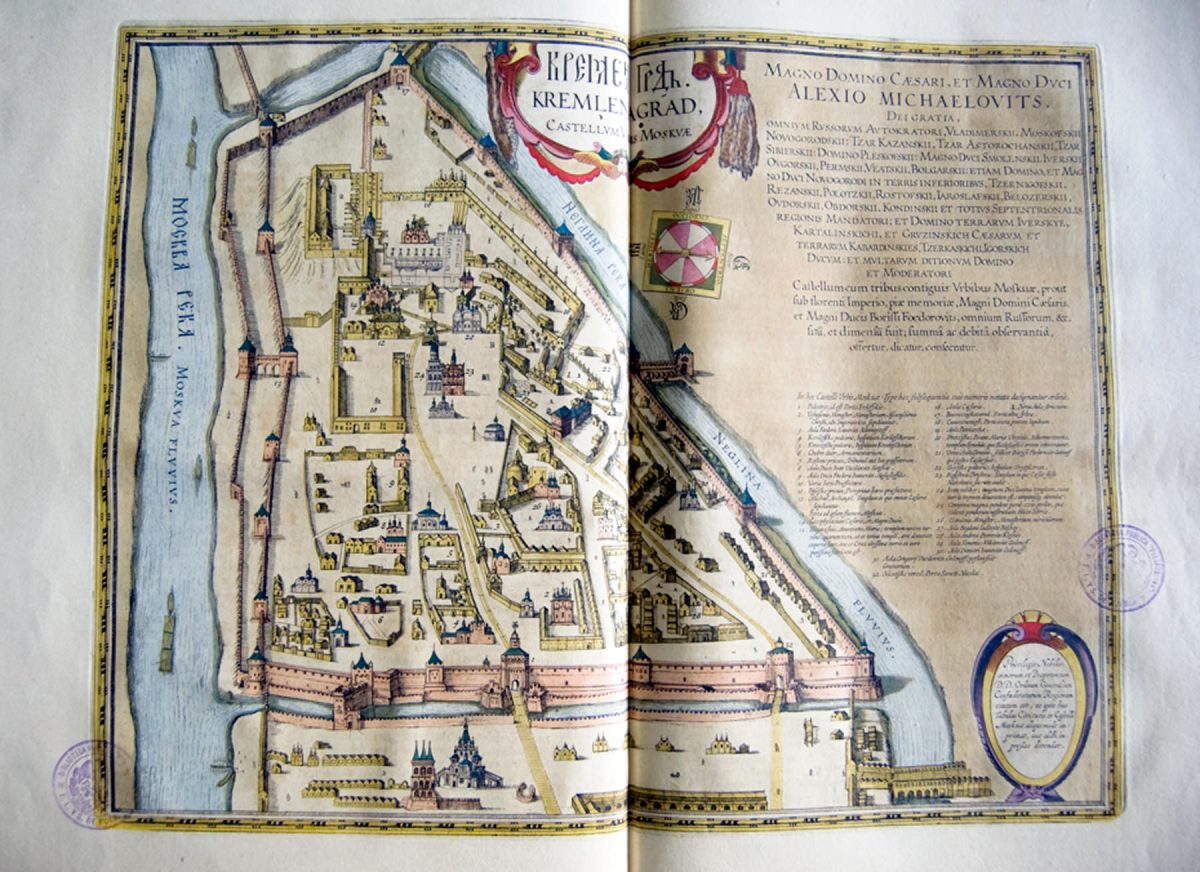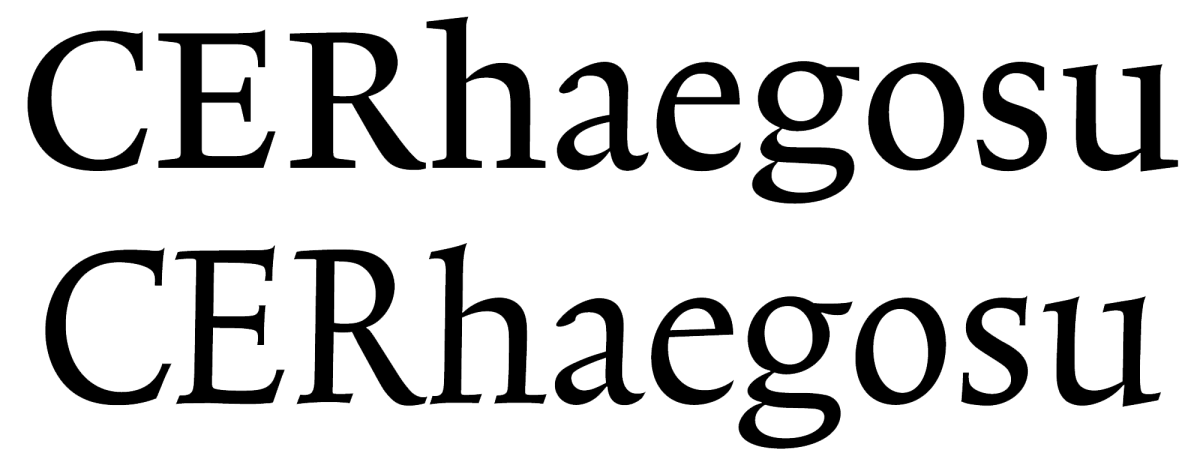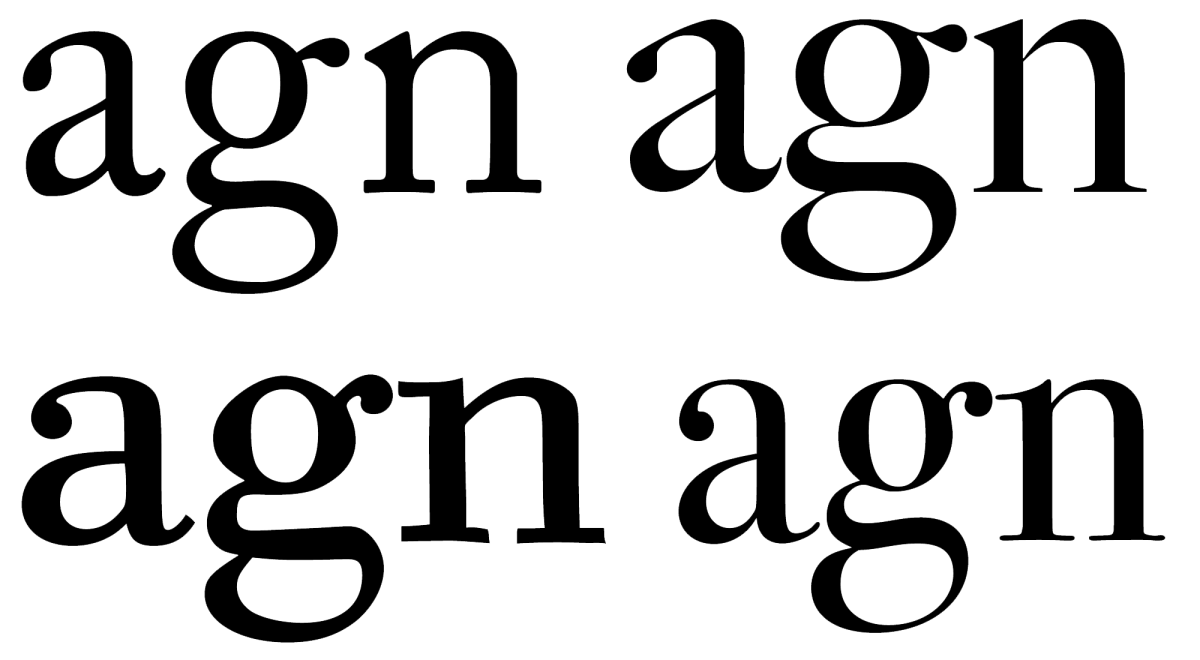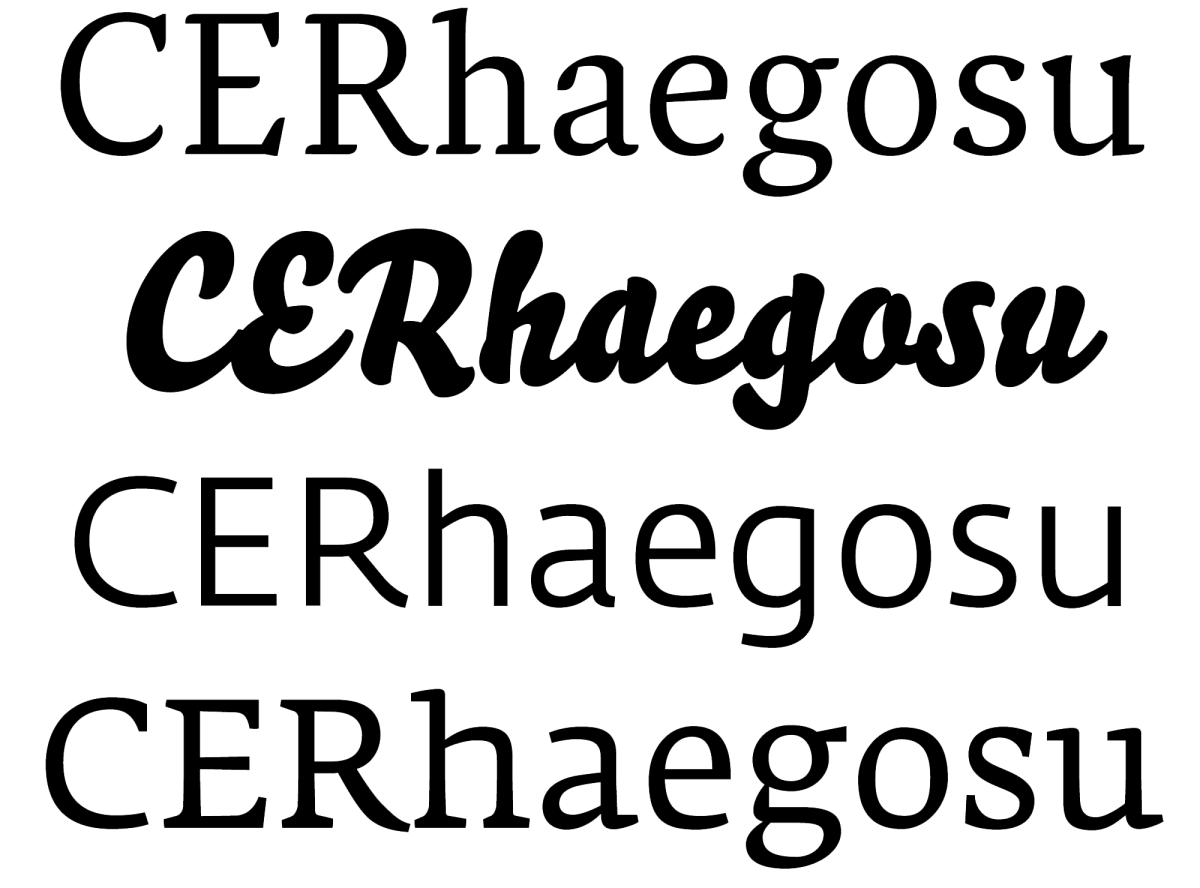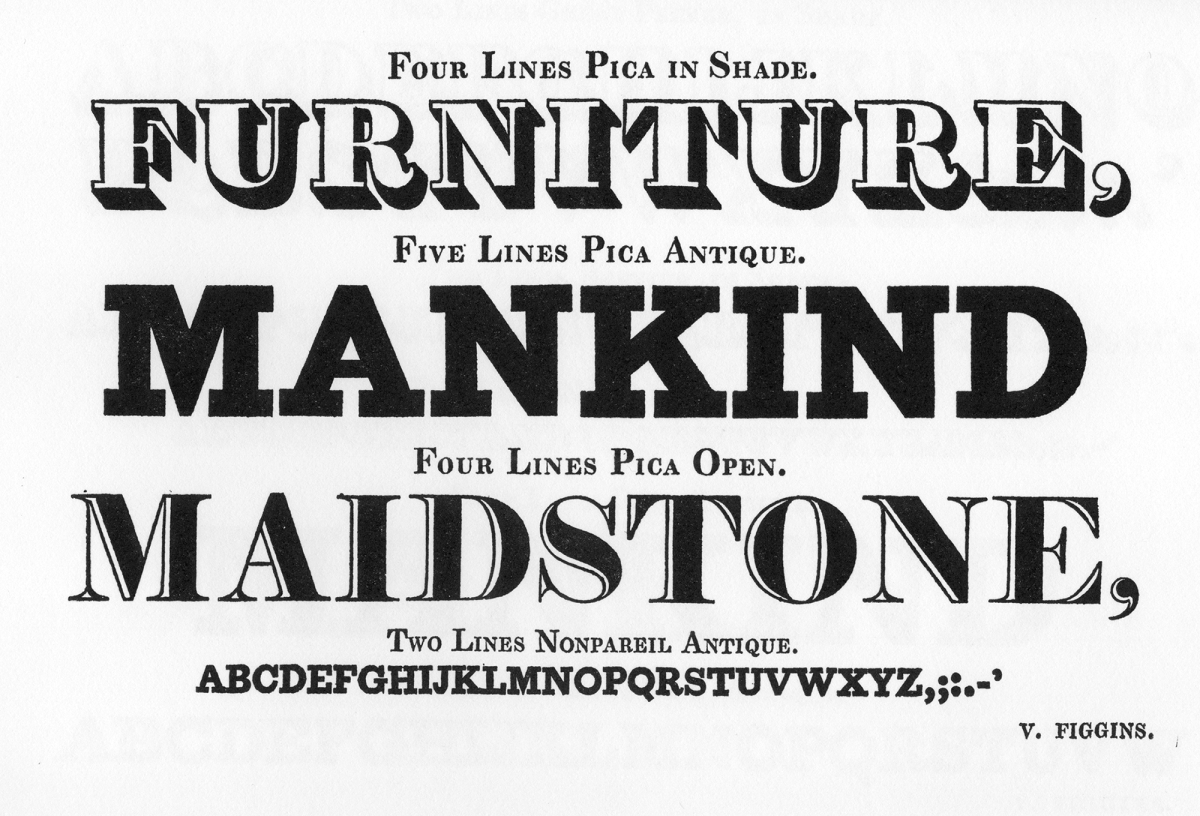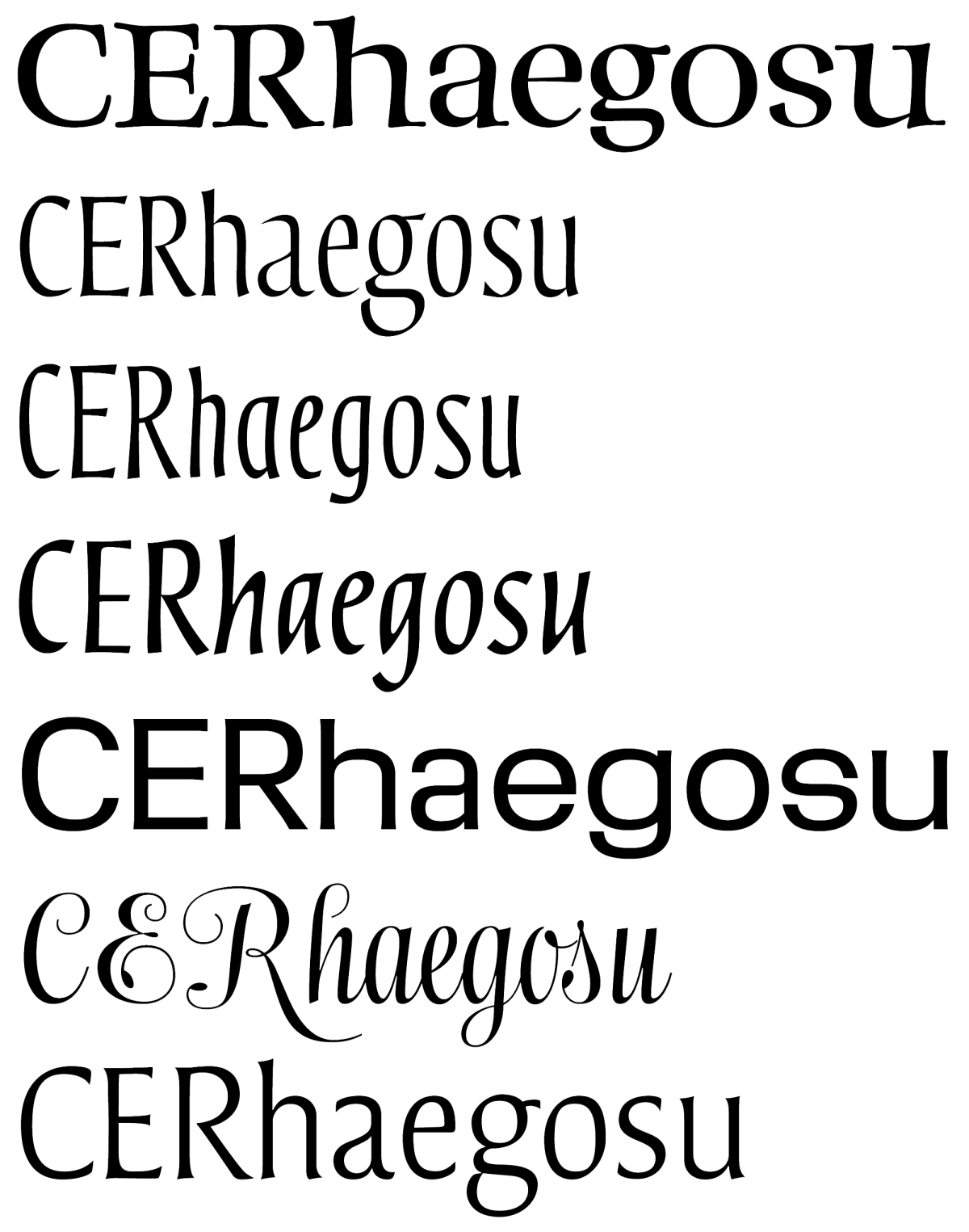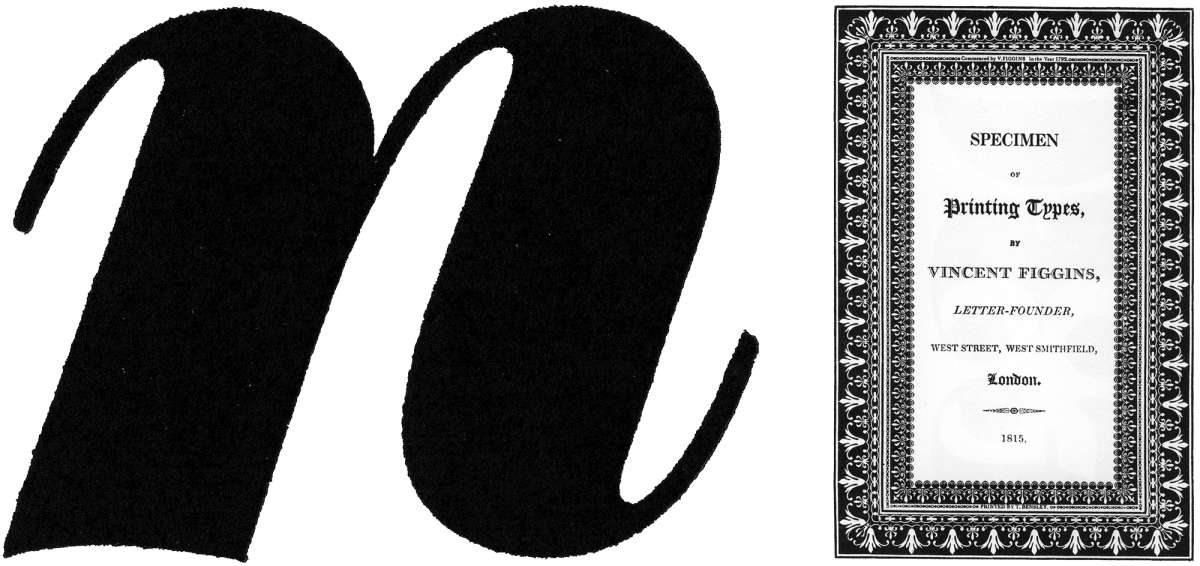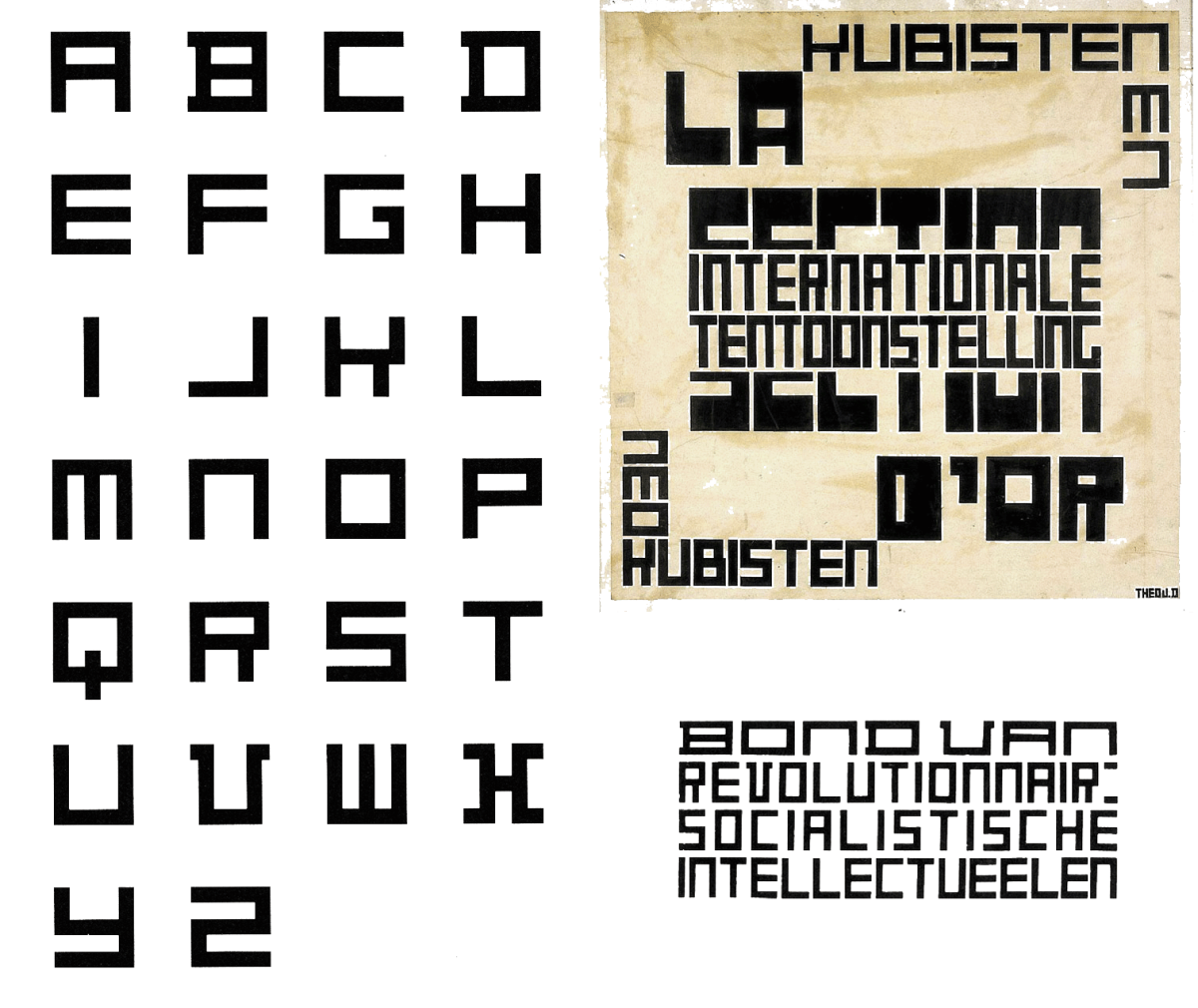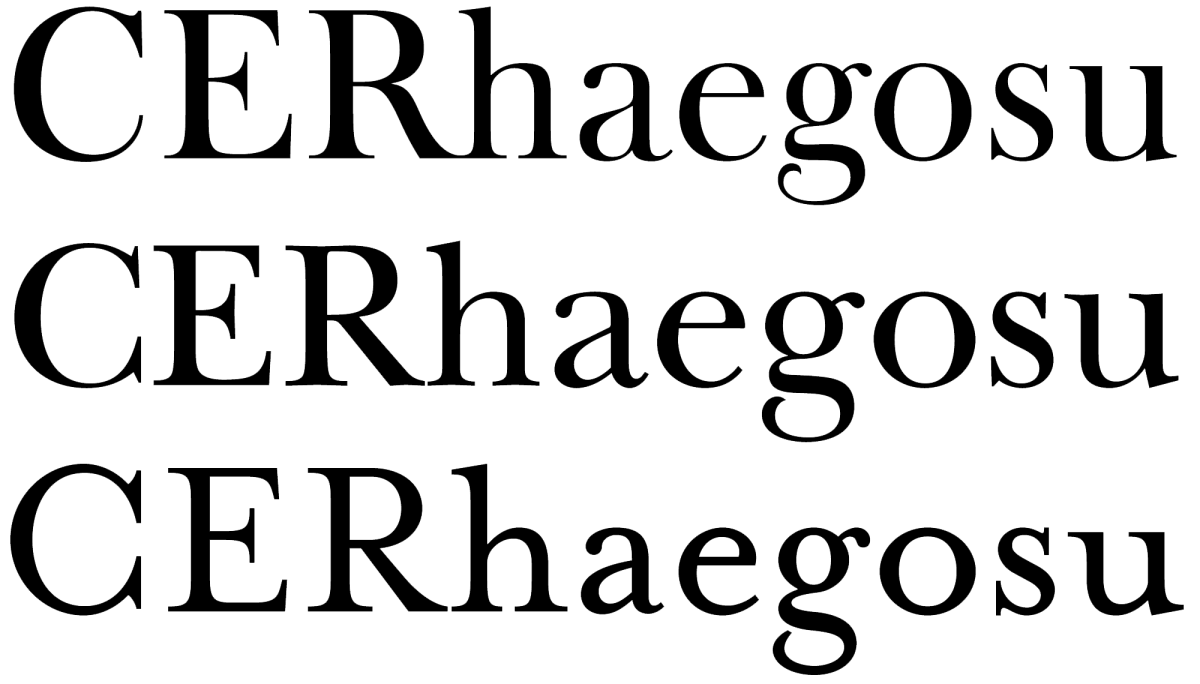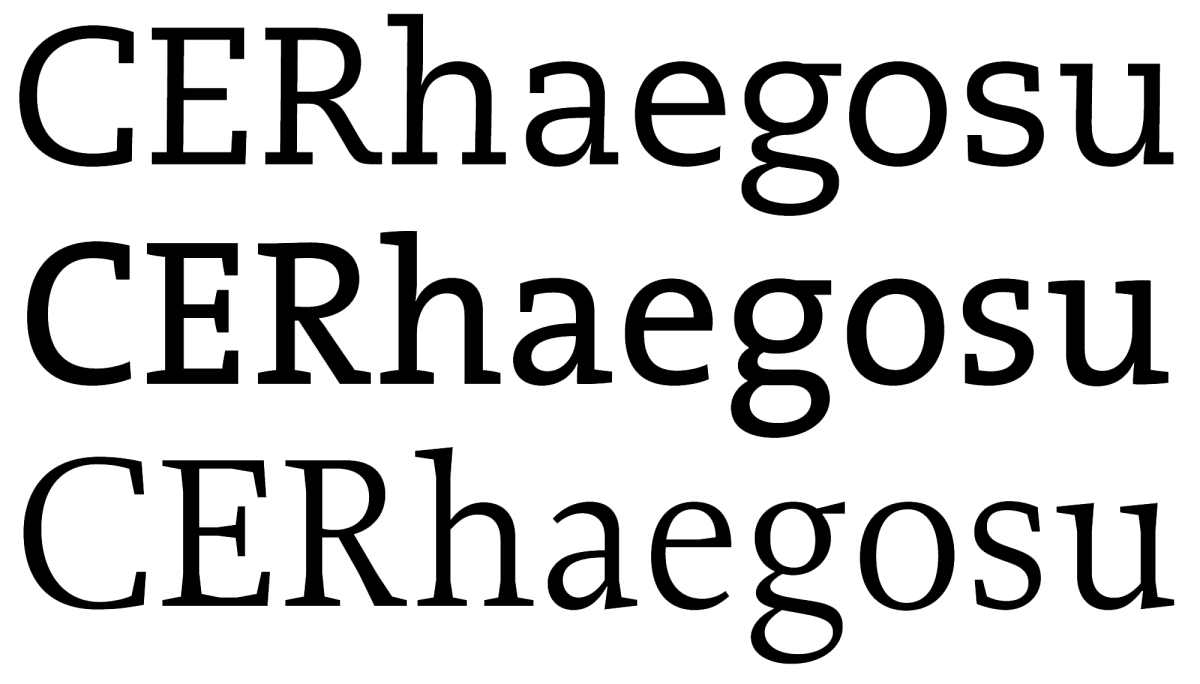
La Herencia Europea. Parte II
Portada de Tipografía en Latinoamérica editado por Blucher, San Pablo, 2013.
Segunda y última entrega del 1er capítulo del libro “Tipografía en Latinoamérica. Orígenes e identidad”, editado por Cecilia Consolo y publicado por Blucher en Brasil, 2013. Sus editores han aceptado amablemente publicarlo aquí. Es una mirada retrospectiva y muy personal de la historia de la tipografía europea desde Gutenberg a la era digital. Pretender abarcar semejante lapso de tiempo en tan poco espacio habilita a posibles exageraciones y reduccionismos. El objetivo ha sido intentar provocar al lector a continuar su propia búsqueda. La primera parte toca en los episodios significativos desde el tipo móvil alemán de fines del s. XV, la escuela humanista italiana, Jenson, Manucio y Griffo, la Edad de Oro francesa del s. XVI, de Tory a Garamond y Robert Granjon. La 2da parte retoma en el barroco neerlandés del s. XVII e intenta referir los hitos fundamentales de la producción británica, ibérica, alemana, y holandesa, incluido el empuje en tipo digital de La Haya. A modo didáctico, imágenes comparativas de anatomía y evolución de las formas tipográficas se han sumado al final de esta 2da parte. (Escrito en Ciudad de México, 10 de enero de 2010.)
Barroco holandés: economía y sentido teatral
La contribución neerlandesa a la historia de la tipografía es una de las más ricas y significativas, desde su edad de oro en el siglo XVII (Barroco) hasta la era digital desde fines del XX cuando La Haya se vuelve uno de los centros de producción y educación tipográficas más influyentes. 1
La rica tradición antigua de la tipografía neerlandesa debe encontrarse en los acerbos de tres grandes imprentas: la Officina Plantiniana (ya mencionada), la casa Blaeu, notable por sus refinadas ediciones cartográficas, y la familia de los Elsevier o Elzevir, una dinastía de impresores de un siglo y medio. Ya citamos a los diseñadores franceses a quienes Plantin encargó tipos. Durante unos 12 años trabajó asimismo para Plantin el talentoso Hendrik van den Keere (1540-1580, también conocido como Henri du Tour). Natural de Gante (Bélgica), Van den Keere grabó romanas y góticas (nunca itálicas) entre 1565 y 1580, y según Fred Smeijers 2 habría hecho la primera romana de cuerpo muy grande, usando para ello punzones de madera sobre matrices de arena. El estilo Van den Keere afirma una tradición holandesa de letras (ya iniciada con Haultin), bastante negras (influenciadas por las góticas), con ascendentes y descendentes más breves y altura de x más generosa, cualidades que habría solicitado el mismo Plantin para ahorrar espacio en sus libros.
La obra de Van den Keere representa una de las colecciones más importantes de la tipografía neerlandesa. Existen dos rescates significativos de la obra de Van den Keere: Renard (1992), realizado por Smeijers y publicado por Enschedé (su redonda es una interpretación delicada y con carácter, respetando el peso original, y su elegante cursiva es una total invención de Smeijers, al no existir fuentes cursivas originales de Van den Keere). El otro rescate fino es DTL Van den Keere (1995) de Frank Blokland, cuyas itálicas se basan en un tipo de François Guyot (c.1557).
Dos rescates históricos holandeses hechos por holandeses: DTL Van den Keere, de Frank Blokland y TEFF Renard, de Fred Smeijers.
La imprenta iniciada de Guillermo y Juan Blaeu está asociada al nombre de un punzonista de Gouda, Nicolaes Briot (leer más sobre Nicolaes Briot en este blog), quien habría grabado unos tipos muy bellos para los textos que acompañaban sus afamados atlas. Estos atlas son los más hermosos, costosos y codiciados de todos los tiempos, sus mapas grabados en cobre y coloreados manualmente a la acuarela. 3
Imprenta de Juan Blaeu: plano de Kremlingrado, Atlas Maior o Geografía Blaviana, coloreado a mano con acuarela como era usual en esa época. Biblioteca Palafoxiana, Puebla, México. Foto: ALC.
La renombrada casa de los Elsevier o Elzevir (cuya reputación —sugiere Sem Hartz 4— parece más el resultado de la repetición del apellido a lo largo de 150 años, que de la apreciación de su calidad más bien estándar) está asociada al nombre de otro talentoso grabador de tipos holandés, Christoffel van Dyck (1605-1669, también “van Dijck”). El estilo de Van Dyck afianza la línea holandesa iniciada por sus predecesores: el contraste entre trazos finos y gruesos es más pronunciado, como lo es el peso de las mayúsculas en relación a las minúsculas (una característica típica del Barroco), logrando un efecto más afilado, preciso y dramático.
Los Elzevir publicaron muchos libros de bolsillo muy pequeños que alcanzaron gran popularidad. Esto hizo que a sus tipos se le llamaran de la misma forma, Elzevir, como se le llama hoy al estilo asociado mayormente a Christoffel van Dyck. Sin embargo los Elzevir utilizaron una gran variedad de tipos de diversa autoría y calidad. Los tipos de Van Dyck fueron muy admirados en Inglaterra, al punto que se convertirían en el modelo a seguir por William Caslon y sus contemporáneos, luego de la promoción favorable que les diera Joseph Moxon. 5. (Más acerca de John Fell en este texto en el apartado “El pragmatismo inglés”.)
De los rescates hechos de los tipos de Van Dyck destacan el de Monotype (versión en plomo a instancias de Stanley Morison en los años 20, y luego en fotocomposición y en digital con la pérdida de calidad esperable). Y el más reciente realizado por Gerard Daniëls para la Dutch Type Library, DTL Elzevir, una interpretación más personal para el entorno digital.
DTL Elzevir, por Gerard Daniëls.
Barroco tardío y madurez de estilo: Miklós Kis
Para John Lane, 6 los punzonistas Hendrik van den Keere, Nicolaes Briot y Christophel van Dyck grabaron los mejores tipos romanos de los Países Bajos y su obra formó el camino fundamental por donde transitó el estilo tipográfico neerlandés durante al menos un siglo. (La obra de Briot está siendo abordada por la fundición PampaType. Ver en este blog The Briot Project. Part I).
Sin embargo el legado tipográfico holandés de la segunda mitad del siglo XVII está profundamente ligado al nombre de un impresor húngaro de importancia clave. Hacia 1680 Miklós Totfalusi Kis (o Nicolás Kis, 1650-1702), nacido en Transilvania, viajó a Amsterdam para encargar a Daniel Elsevier la impresión de la primera biblia en húngaro. Pero al llegar éste había muerto y Kis se dispuso a hacer el trabajo él mismo. En un lapso de sólo 9 años aprendió a fundir tipos (bajo la tutela de Dirk Voskens), estableció su propia imprenta, e imprimió su biblia y varios libros más, siempre empleando sus propios tipos, los cuales alcanzaron gran fama en toda Europa. Su trabajo permaneció velado bajo el nombre del fundidor holandés Anton Janson, quien incluyó tipos de Kis en uno de sus especímenes. En 1953 George Buday y Harry Carter revelaron que se trataba de la obra de Nicolás Kis. 7 Luego de su estancia en Amsterdam Kis regresa a Transilvania y se re-instala como impresor, aunque no obtiene el respeto de sus conacionales, y su obra es rescatada del olvido recién a mediados del siglo XX.